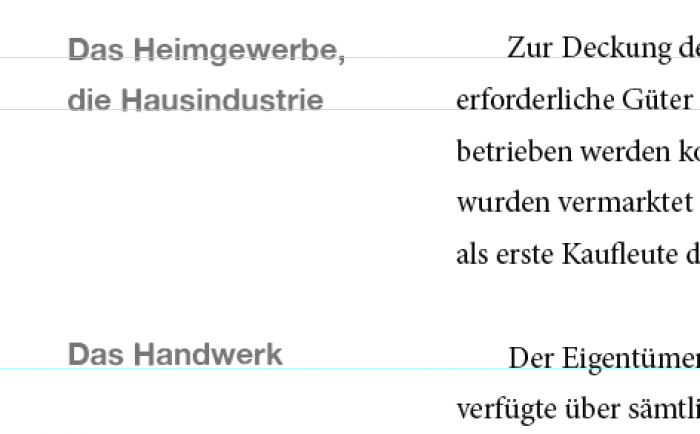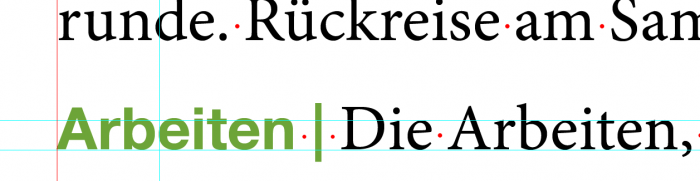
Irgendwas stört mich
vorab: Ich bin kein Profi. Komme aus einem anderen Bereich der Kreativen. Habt also bitte etwas Nachsicht.
Meine Frage ist einfach ob die abgebildeten Schriften gut zusammen gehen? Minion Pro mit der Alten Haas Grotesk. Die Schriften sind noch nicht auf Grundlinienraster.
Bin auch kein Profi, aber die Marginalien scheinen mir direkt von hinten ins Knie gegrätscht. Hast du einen Schnitt, der etwas leichter daherkommt?
die beiden gehen ganz gut zusammen. (ich persönlich bevorzuge die neue helvetica zur minion.) «störend» ist in deinem muster allenfalls, dass die serifenlose, starke, laute grotesk die leisere serifenschrift doch sehr kräftig übertrumpft. nimm die haas in der größe einen tick zurück und es wird dich nichts mehr stören. im angehängten beispiel ist die minion in 10 und die neue helvetica bold in 9 punkt versetzt.
Mich stört
1) das optische Übergewicht der Marginalien, das könnte man – wenn es denn kein anderer Schnitt sein soll – mit einem Grau statt schwarz hinbekommen
2) dass die Marginalien nicht auf der Grundlinie des Texts stehen
Vielleicht macht auch der Erstzeileneinzug die Sache unnötig unruhig. Dass an den entsprechenden Stellen etwas Neues beginnt, wird ja bereits durch die Leerzeile davor und das Stichwort in der Marginalspalte ausgedrückt. Auf den Erstzeileneinzug könnte man also verzichten.
Das Türkis halte ich übrigens für gewagt, da sehr hell. Der Textteil rutscht eher durch, als dass er betont wird. Vielleicht würde auch eine Auszeichnung (Farbe oder Schrägstellung) genügen.
Tut mir leid, wenn ich so "doofe" Fragen stellen muss. Aber gibt es eine bestimmte Regel für das Verwenden unterschiedlich großer Schriften? In dem Bsp. oben seht ihr 9pt Größe mit 15pt Zeilenabstand. Was gebe ich nun den Überschriften? Und vor allem: Wie gehe ich dann mit dem Grundlinienraster um (bei unterschiedlichen Schriftgrößen) ?